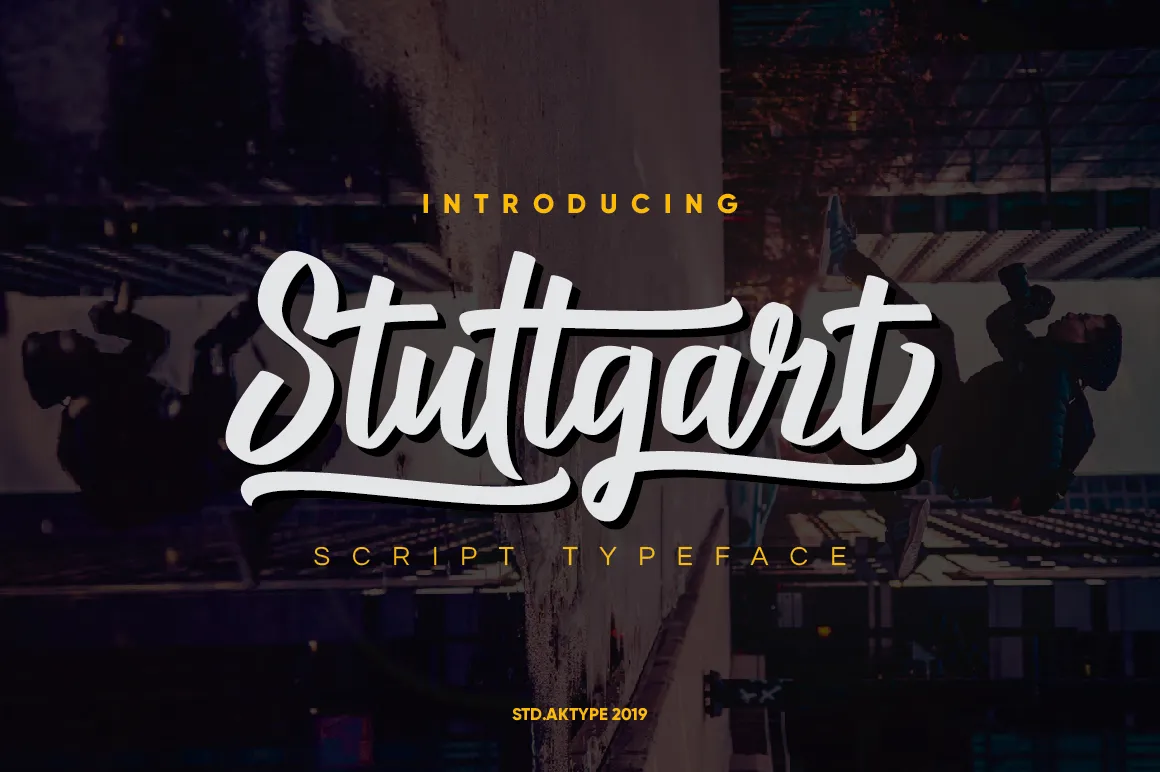
Stuttgart Script Font
A fonte Stuttgart Script é perfeita para quem procura uma fonte elegante e fluida para projetos criativos. Se você está buscando algo que se destaque, esta fonte é a escolha certa para seus próximos trabalhos de design. Ideal para criar logos, rótulos de camisetas ou marca personalizada, Stuttgart Script oferece um estilo chamativo que se assemelha a escrita à mão. Suave e delicada, essa fonte também é versátil o suficiente para ser usada em uma variedade de materiais impressos. Seja você usando técnicas de gravação de metal ou bordado, essas letras ficam perfeitamente elegantes. Além disso, a Stuttgart Script não precisa de adesivos adicionais para seu design, pois é forte e resistente o suficiente para ser usada em uma ampla variedade de materiais. O designer Studio Aktype criou esta fonte para designers que desejam algo novo e interessante para seus trabalhos. Com sua forma elegante e fluida, ela será um ótimo adição a qualquer projeto de design. Esta é uma fonte para quem está sempre procurando por opções únicas e criativas, perfeita tanto para novatos quanto para designers experientes que desejam trazer um toque único ao seu trabalho.